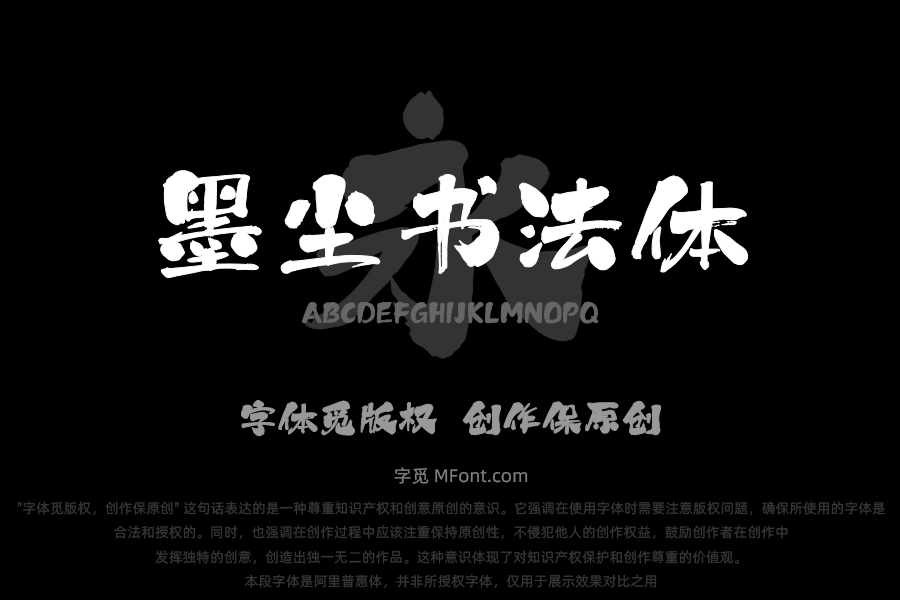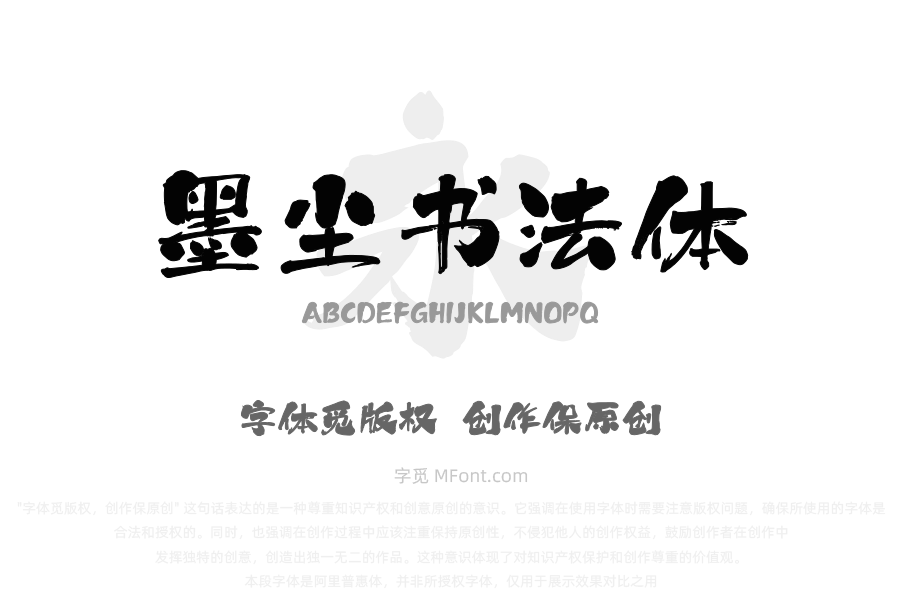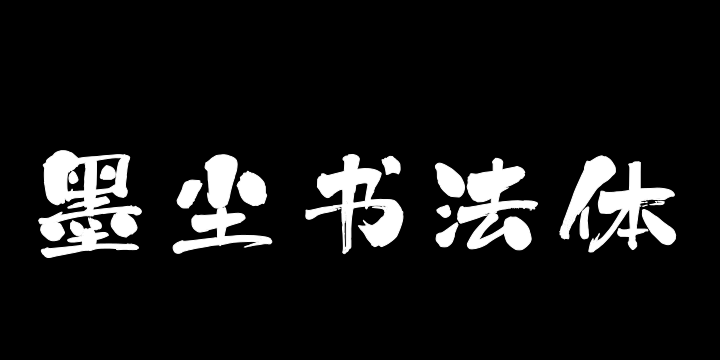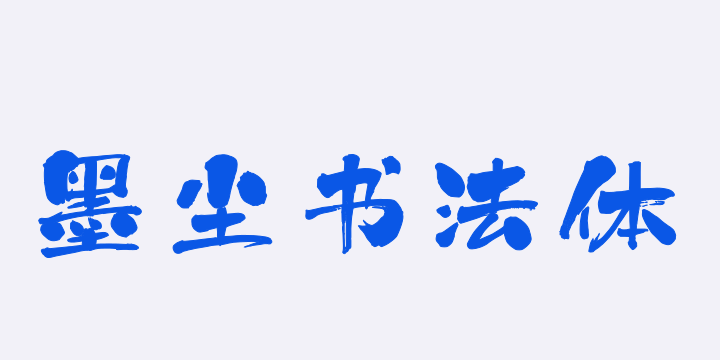
• 上首墨尘书法体
字体全名: 上首墨尘书法体
字体简介: 上首墨尘书法体,简体中文约6763字,在笔画形态上采用粗细交替的处理方式,粗笔如磐石般沉稳厚重,细笔则似游丝般轻盈灵动。字体结构紧凑有序,通过巧妙的笔画穿插,让字与字之间相互呼应,浑然一体。毛笔笔画留下的飞白痕迹,更是增强了字体的节奏感与韵律美。适用于搭配标志、广告标语、商业广告等高端属性。